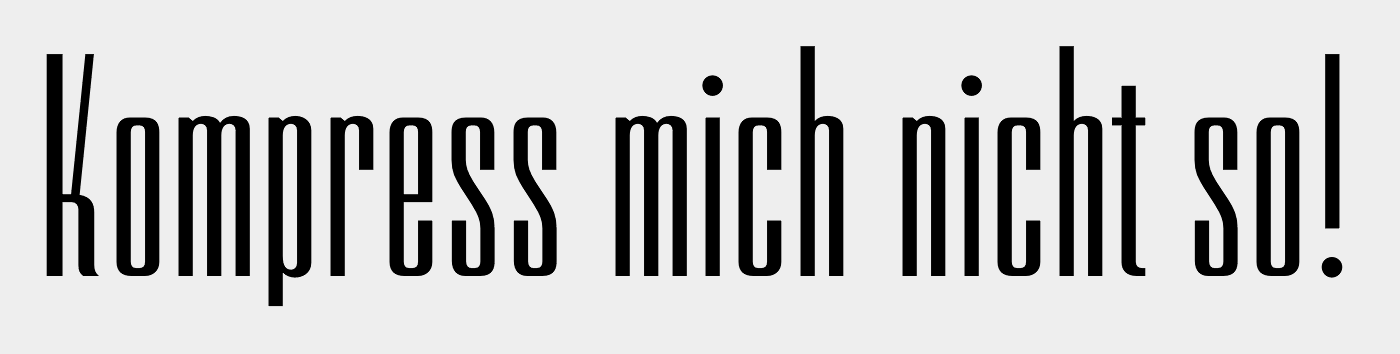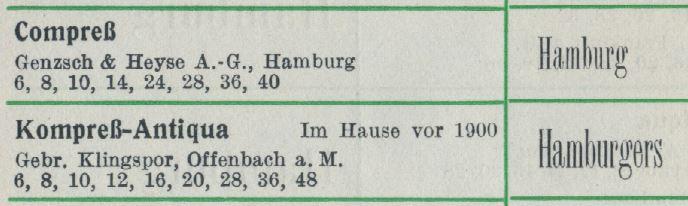
Und was steht im Wörterverzeichnis 2006 unter »kompress«?
Das ist irrelevant, weil der Duden kein Fachwörterbuch der Satztechnik oder Typografie ist. Er verwendet kompress aber sehr wohl als "eng stehend" auch horizontal, wie das Zitat daraus belegt: "Strich und Ortsbezeichnung werden dabei ohne Zwischenraum miteinander verbunden, d.h. kompress gesetzt."
… Den Satz ein wenig »kompresser« machen, die »kompresseste« Kolumne von allen, das geht nicht. …
Den Zeilenabstand ein wenig »kompresser« machen geht aber schon? 8-)
Bei Schriften mit einem „Kompress“ im Namen geht man auch nicht davon aus, dass diese mit wenig Durchschuss gesetzt werden müssen :-D
Gibt es außer dieser hier noch andere? :-? (Ich nehme mal an, dass du keine Schriften meinst, die »compressed« im Namen haben, denn auf Englisch hat das schon noch eine leicht andere Bedeutung.)
Aber nun kennen wir wahrscheinlich wenigstens Ralph Ungers Position in dieser Frage.
Nein. »Ohne« heißt nicht »weniger«. Und eine andere Definition als »ohne Durchschuß« wird man nicht finden. Oder?
Doch, wird man: "ohne zusätzlichen Abstand". Eben wie das Wort kompress heute allgemein verwendet wird. Dass das zu deinen Lehrzeiten enger gefasst war, bestreitet ja niemand.
Sogar die der Amt für Veröffentlichungen der EU kennt es in ihren "interinstitutionellen Regeln für Veröffentlichungen".
Gibt es außer dieser hier noch andere?
Ich habe die ganze Zeit alte Letraset-Bögen vorm Auge – muss also schon etwas länger her sein.
Und Tante Google ist da gerade auch nicht hilfreich.
Eine habe ich noch gefunden, im Seemann gibt es eine Schrift mit dem Namen „Kompreß-Antiqua“. Konnte aber online kein Schriftmuster dazu finden.
Nun ja, ich kann mir durchaus eine Anwendung außerhalb der Druckbranche vorstellen: "Auf dem Autofrachter nach Afrika werden die alten Gebrauchtwagen kompress verladen." Das wär sicher verständlich und niemand würde annehmen, dass sie ohne Durchschuss übereinander stünden.
Und generell, ist nicht eigentlich jeder Fachbegriff einst einmal eine Privatdefinition gewesen, die dann ein Meister seinen Lehrlingen vermittelte, diese dann in andere Betriebe weiter trugen, bis schließlich ein Fachbegriff daraus geworden ist - und dann, bei genügend Belegen für die Verwendung ins Wortverzeichnis des Duden wandert.
Ändert sich dann die Technik, und immer mehr Leute nutzen den Begriff dann in einem anderen ähnlichen Zusammenhang, dann wandelt sich eben der Begriff, und irgendwann auch die Bedeutungsbeschreibung im Duden. So funktioniert eine lebende Sprache nun einmal
Dann irrt der Duden mit seiner Beschreibung des Wortes als veraltet? Und nach hier herrschender Meinung beschreibt das Wort als Fachbegriff einen Schriftsatz »ohne zusätzlichen Abstand« hinsichtlich des Durchschusses und für den Fall der Gedankenstrichanwendung als »bis«. Verstehe ich das richtig? Und definiert ist das als Fachbegriff trotz institutioneller, womöglich amtlicher Anwendung außerhalb von Wikipedia nirgends?
Ich kann mir vorstellen, daß der Begriff als falsche Übersetzung aus dem Englischen seine Bedeutung bekommen hat. So wie »Gewicht« für »Schriftschnitt«. Oder »Typo« für »Schrift«. Wird ständig verwendet, vor allem hier. Wird sicherlich demnächst in Wikipedia auftauchen. Oder ist es schon?
Eine habe ich noch gefunden, im Seemann gibt es eine Schrift mit dem Namen „Kompreß-Antiqua“. Konnte aber online kein Schriftmuster dazu finden.
Es gibt eine Compreß von Genzsch & Heyse, ohne Jahr, und eine Kompreß-Antiqua von Klingspor mit der Angabe »Im Hause vor 1900«. Die Schriften laufen sehr eng und stehen auf einer Seite mit der Engen Akzidenz-Antiqua, der Engen Antiqua, der Schmalen schlanken Antiqua usw. Das ist also die exakte Übertragung der allgemeinen Bedeutung des Wortes »eng«. Mit der Fachsprache muß es nichts zu tun haben. Aber auch: Wolfgang Beinert ohne Angabe von Quellen: »Der Begriff »kompreß« wird in älteren Typographielehrbüchern vereinzelt auch für eine sehr enge Schriftlaufweite ohne Auszeichnungen verwendet.« Das wiederum bezieht sich nicht auf Spationierung in der Zeichensetzung.
Wenn jemand ein typografisches Fachbuch findet mit der EU-amtlichen Anwendung, das wäre ja mal ein Anhaltspunkt.
Dieter, du meinst, der Duden verwendet in seiner aktuellen Ausgabe ein Wort, das er selbst als veraltet definiert? Und zwar veraltet seit Jahrzehnten? Denn auf die fachsprachliche Dudendefinition kann sich die Anwendung nicht beziehen.
Der andere Punkt ist, daß das Wort fachsprachlich keine klare Definition mehr hat, so wie der Duden es im satztechnischen Teil verwendet.
2. Halte ich, wie oben beschrieben, in diesem Zusammenhang den Duden nicht wirklich für den Quell der unendlichen Weisheit
3. Habe ich anderes zu tun, als ›kritisch‹ zu recherchieren, ob die Experten (in diesem relativ belanglosen Fall*) Recht haben – z. B. Spazierengehen ...
* Ich glaube kaum, dass der Begriff mit der mir neuen Bedeutung jetzt in meinen täglichen Sprachgebrauch eingegangen ist. Selbst in der anderen Bedeutung schlummert er eigentlich irgendwo ganz hinten als Hintergrundwissen, ohne dass ich ihn aktiv benutze ...